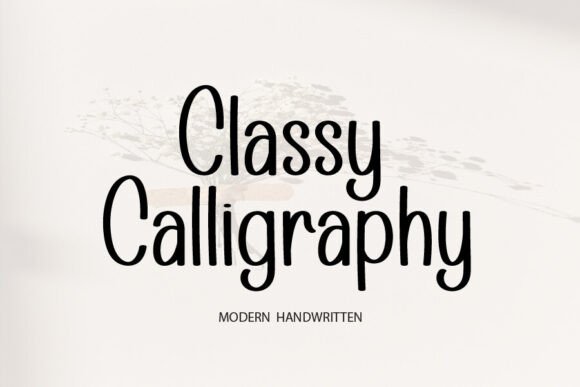
Classy Calligraphy
Поиск подходящих элементов дизайна может быть сложным, но Classy Calligraphy предлагает исключительную коллекцию, которая мгновенно улучшит вашу работу.
Создаете ли вы продукты POD (печать по требованию), свадебные приглашения или графику для социальных сетей, Classy Calligraphy станет идеальным выбором.